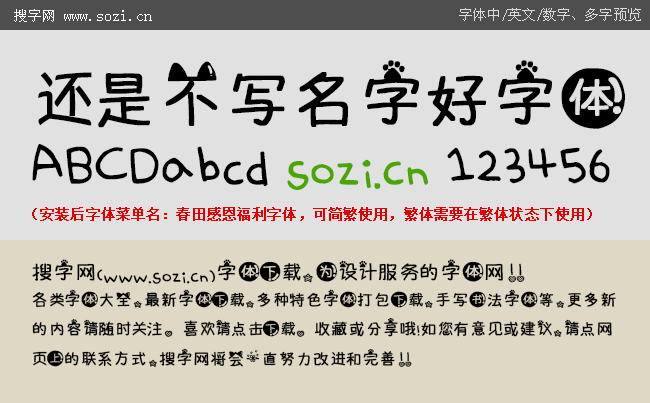
還是不寫名字好字體
搜字網(wǎng)給大家提供一款卡通手寫風(fēng)格的手機中文字體下載。名字叫還是不寫名字好字體,這款手機字體是仿照兒童手寫風(fēng)格的卡通手寫字體,結(jié)構(gòu)帶有POP字體風(fēng)格,字體間還插入了大量有趣卡通圖案,特別適合喜歡手機字體個性一些的朋友在手機上安裝使用。